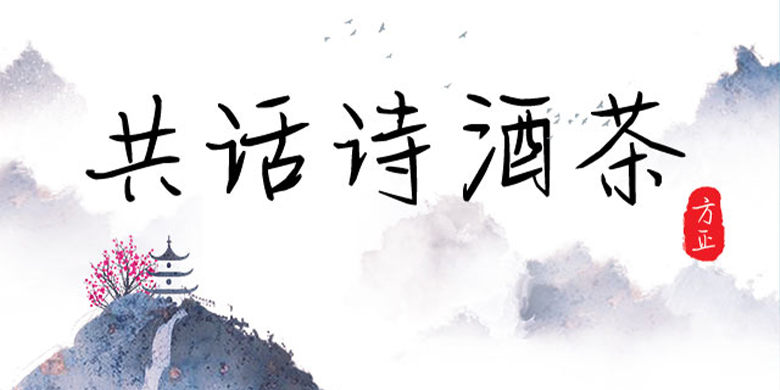
方正手迹-共话诗酒茶
方正手迹-共话诗酒茶,这款字体结构工整、笔画清晰,兼顾美观与易读性,适用于标题、正文、海报、包装、LOGO 等多种场景。字形优雅稳定,风格百搭耐看,适配日常排版与创意设计,让文字呈现更舒适、更具质感。方正手迹-共话诗酒茶一笔一画,皆是细节,以均衡的比例、流畅的线条打造舒适视觉体验,字形端正大气,风格简约现代。无论是商业设计、品牌宣传还是日常排版,都能轻松驾驭,让文字更有格调与力量。方正手迹-共话诗酒茶字体下载。
字体品牌: 方正手迹 设计师:刘殿儒 字体分类:常规书写·硬笔 字体属性:精品字 字符集:大陆简体(GB2312-80) 发布时间: 2020
共话诗酒茶这款字体笔法丰富,有很多传统书法的影子。字形中宫紧收,主笔适当伸长,独具韵味。适用于文艺类的书刊、品牌广告和产品包装设计,以及社交网络的个性化用字。